Tipografía
Es la disciplina que dentro del Diseño Gráfico estudia los distintos modos de optimizar la emisión gráfica de mensajes verbales.
Tipografía
Tipo es la forma o diseño de una letra determinada.
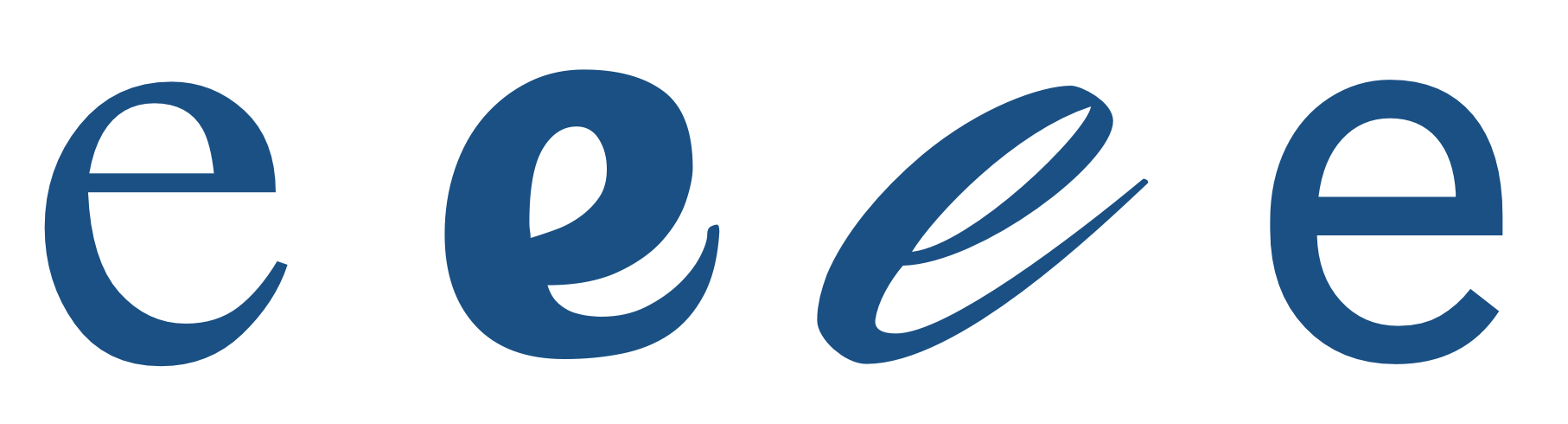
Fuente tipográfica es la que se define como estilo o apariencia de un grupo completo de caracteres, números y signos, regidos por unas características comunes.
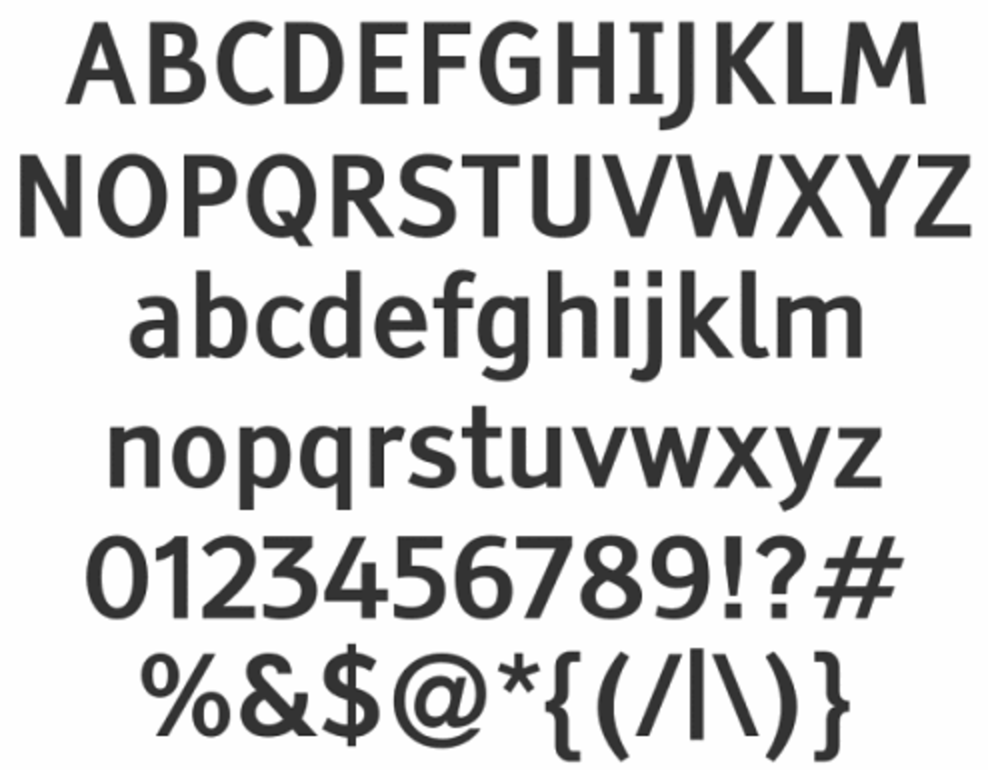
Familia tipográfica, es conjunto de tipos basado en una misma fuente, con algunas variaciones, pero manteniendo características comunes.
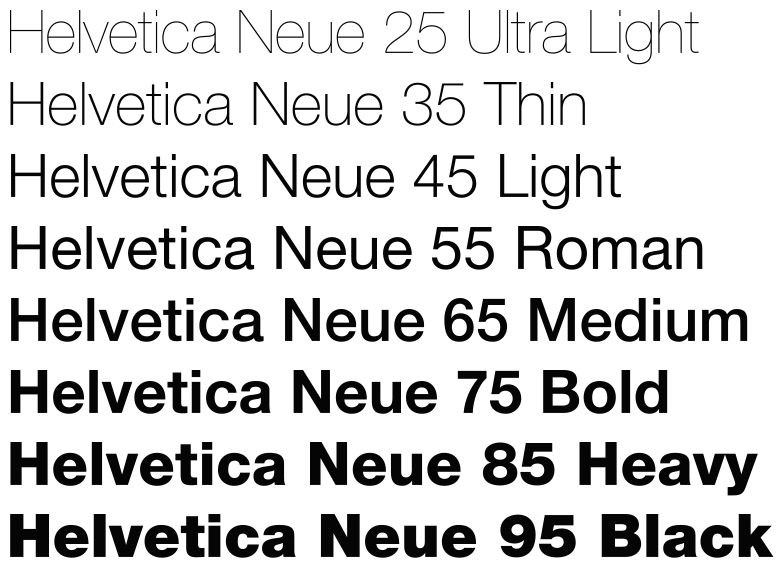
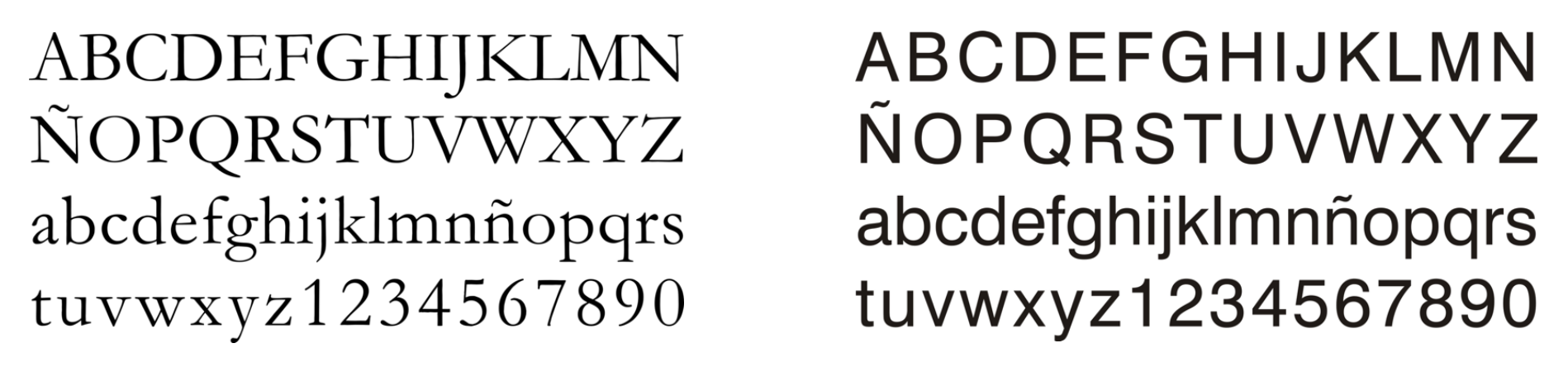
Diferencias
· La presencia o ausencia del serif.
· La forma del serif.
· La relación curva o recta entre bastones y serifs.
· La uniformidad o variabilidad del grosor del trazo.
· La dirección del eje de engrosamiento.
Elementos para clasificar a las diferentes tipográfias:
Clasificación de las familias tipográficas
Romanas
antiguas
Romanas
de transición
Romanas
modernas
Egipcias
Serif
Sin serif
[Palo seco]
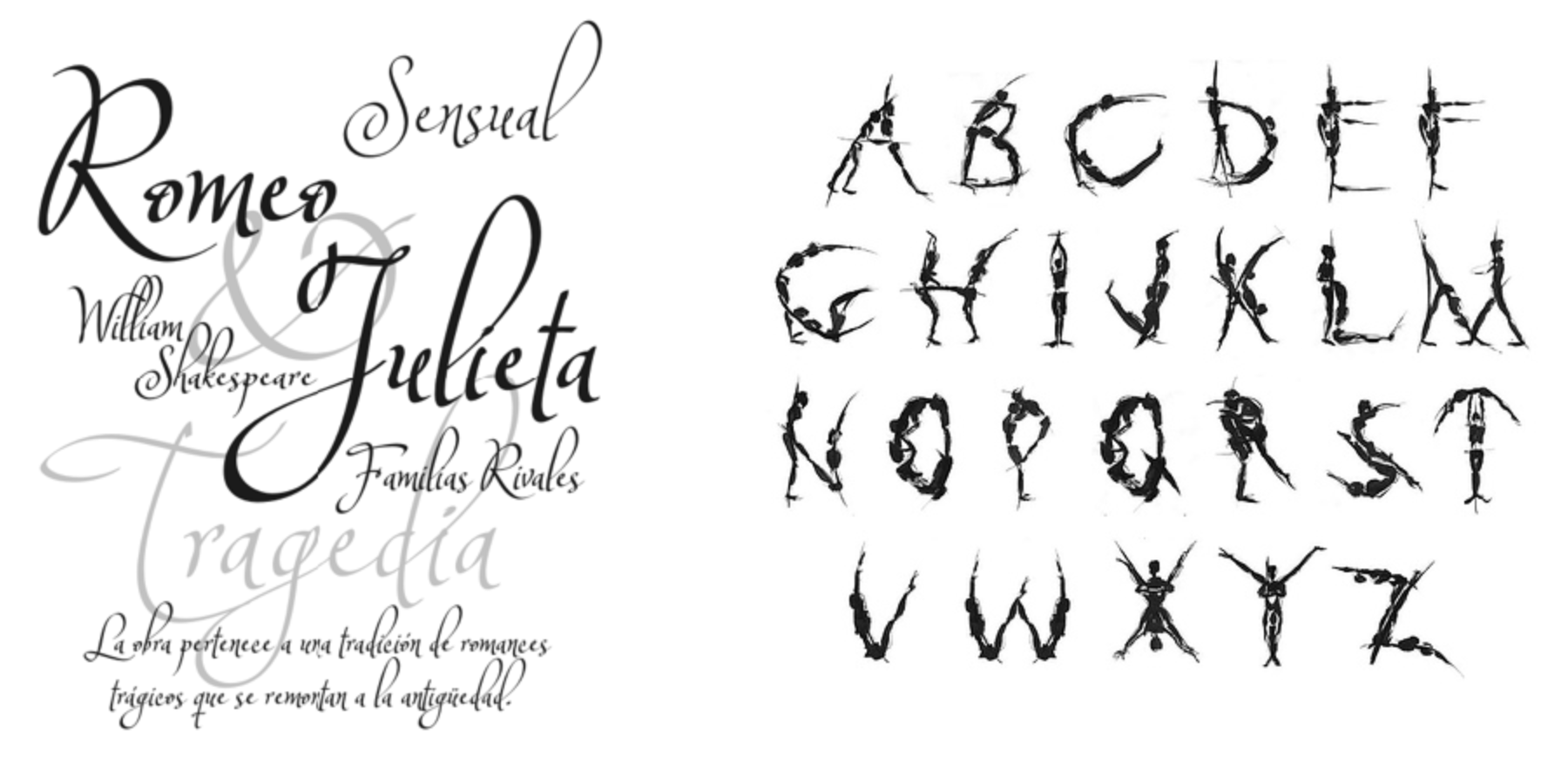
Clasificación de las familias tipográficas
Caligráficas
Fantasía
La lecturabilidad es la facilidad con la que el texto puede ser leído
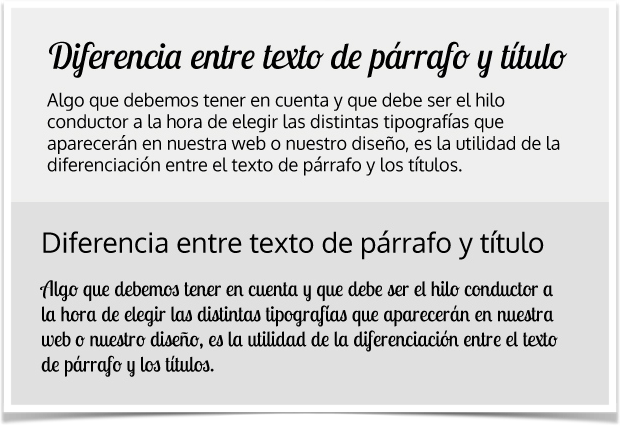
Lecturabilidad
Izquierda
Derecha
Centro
Justificado
Alineado
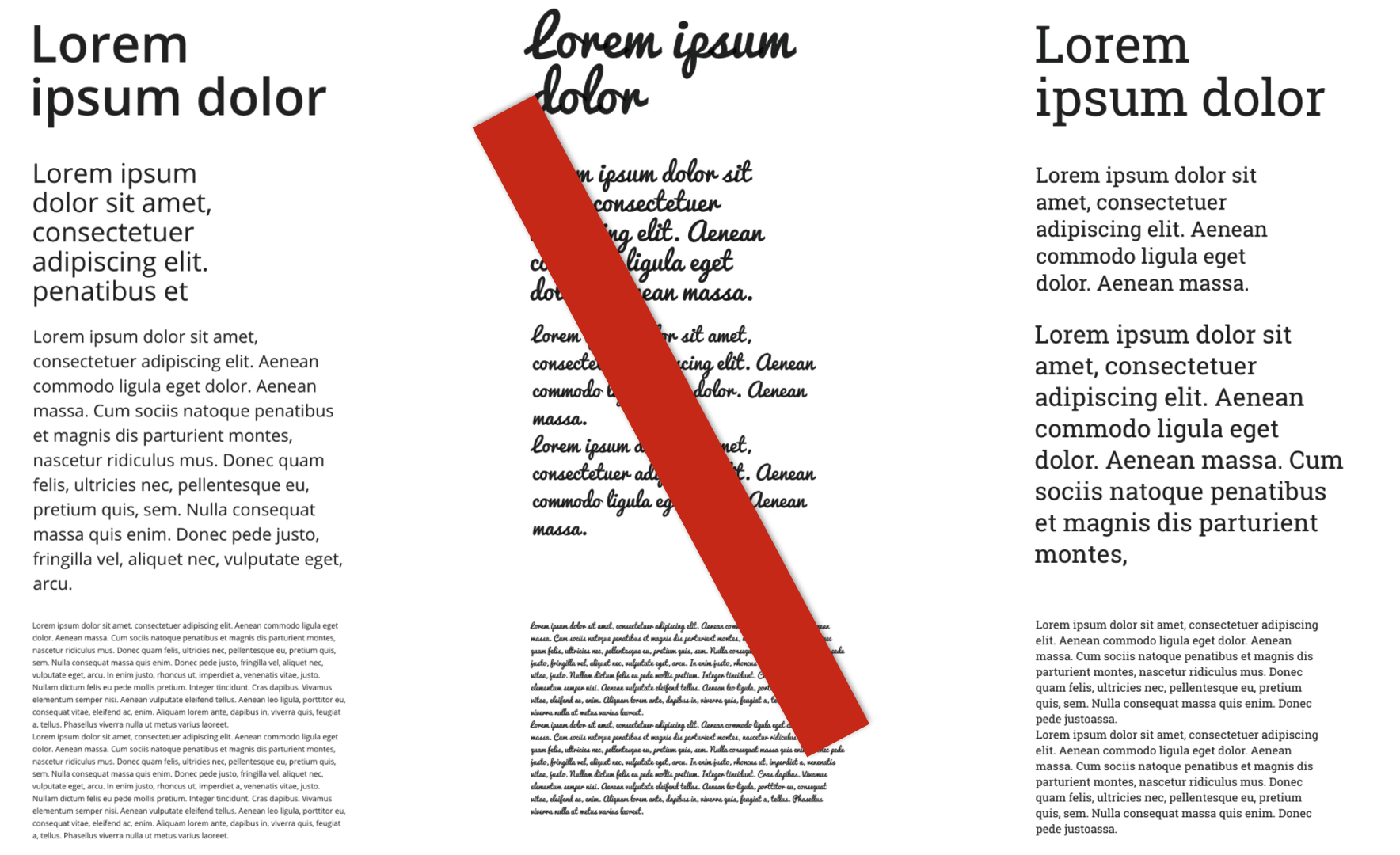
Combinar fuentes
Tipografía en pantalla
Una pantalla es una retícula de píxeles. Pueden ser puro blanco y negro o en subpíxeles de RGB (Red, Green y Blue). Por el principio de mezcla aditiva (colores luz) se obtienen los demás colores
Tipografía en pantalla
PT Sans + Serif
Alegreya sans + serif
Tipografía en pantalla
Roboto + slab
Noto sans + serif
Es la zona segura visible de títulos y textos en pantalla.
Uso de márgenes de títulos seguro